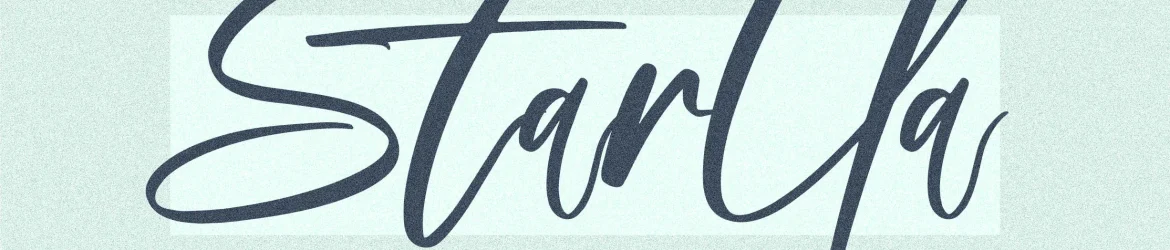
Starlla Font
A fonte Starlla é perfeita para aqueles que procuram uma atmosfera natural e envolvente para seus projetos. Esta elegante fonte manuscrita traz um toque autêntico a qualquer projeto, seja criando logos vibrantes ou designs de embalagens sofisticadas, incluindo mugs com desenhos pessoais ou até mesmo envelopes de festa com texturas únicas. Com Starlla em mãos, você pode criar uma variedade imensa de itens, desde cartões de nome e convites elegantes até etiquetas de pratos e capas de livros para colecionadores. Além disso, a fonte enriquece seus projetos digitais com um toque autêntico, fazendo o texto em sua foto ou vídeo ganhar vida. Seja você um fotógrafo criando trabalhos finamente detalhados, designer gráfico buscando dar um tom distintivo a seu design de produto ou artista que busca texturas e tons únicos para seus trabalhos digitais, Starlla é uma ótima escolha. Com o Designer perspectype, Starlla oferece uma maneira única de personalizar cada projeto. Com sua abrangência em variedades de projetos — desde homewares até grandes eventos especiais — essa fonte manuscrita traz um toque autêntico e único aos seus trabalhos digitais ou físicos. Seja você um designer gráfico, fotógrafo digital ou simplesmente alguém que aprecia uma fonte com o encanto de um texto bem escrito a olho nu, Starlla é sua escolha perfeita.